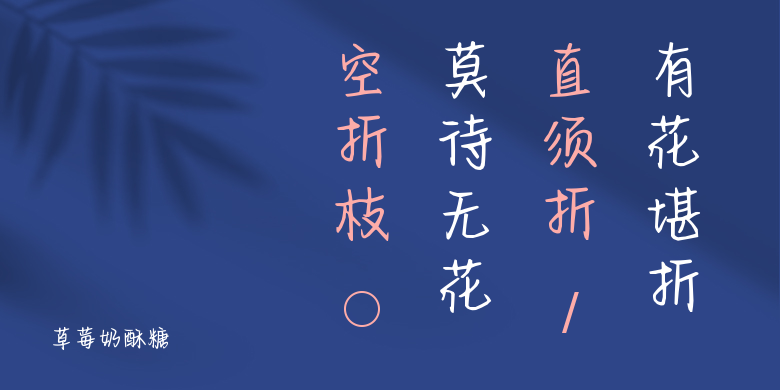
草莓奶酥糖
草莓奶酥糖,这款字体结构工整、笔画清晰,兼顾美观与易读性,适用于标题、正文、海报、包装、LOGO 等多种场景。字形优雅稳定,风格百搭耐看,适配日常排版与创意设计,让文字呈现更舒适、更具质感。草莓奶酥糖一笔一画,皆是细节,以均衡的比例、流畅的线条打造舒适视觉体验,字形端正大气,风格简约现代。无论是商业设计、品牌宣传还是日常排版,都能轻松驾驭,让文字更有格调与力量。草莓奶酥糖字体下载。